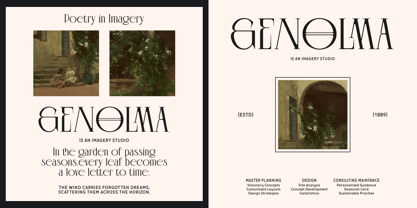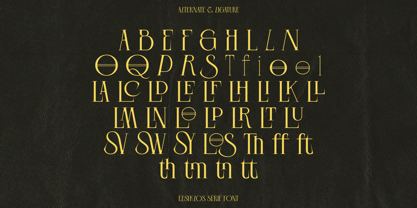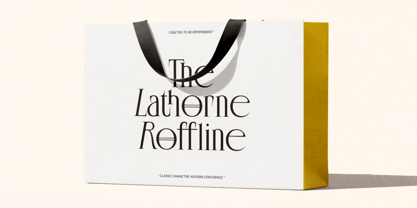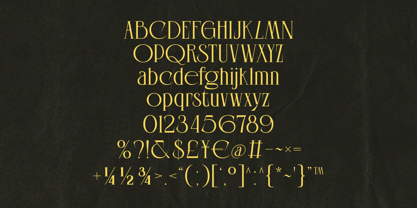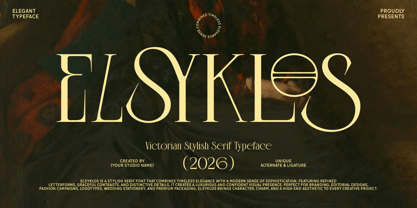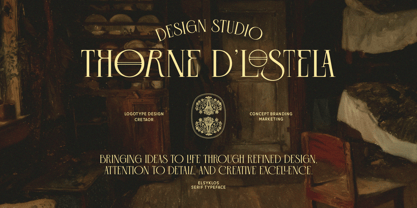
Elsyklos
Elsyklos is a decorative display serif with a formal Victorian mood and strong contrast between thin hairlines and broad, curved strokes. Its letterforms mix tall vertical stems, sharp wedge-like serifs, rounded bowls, and flowing Art Nouveau-style curves, giving the alphabet a ceremonial rhythm. Several characters include ornamental alternates, swash-like shapes, and connected ligatures that make the font more expressive in short settings. The spacing appears fairly tight and the design is most readable at large sizes. Elsyklos suits titles, logos, editorial headers, wedding stationery, packaging, fashion layouts, and poster typography where a dramatic serif style is appropriate.